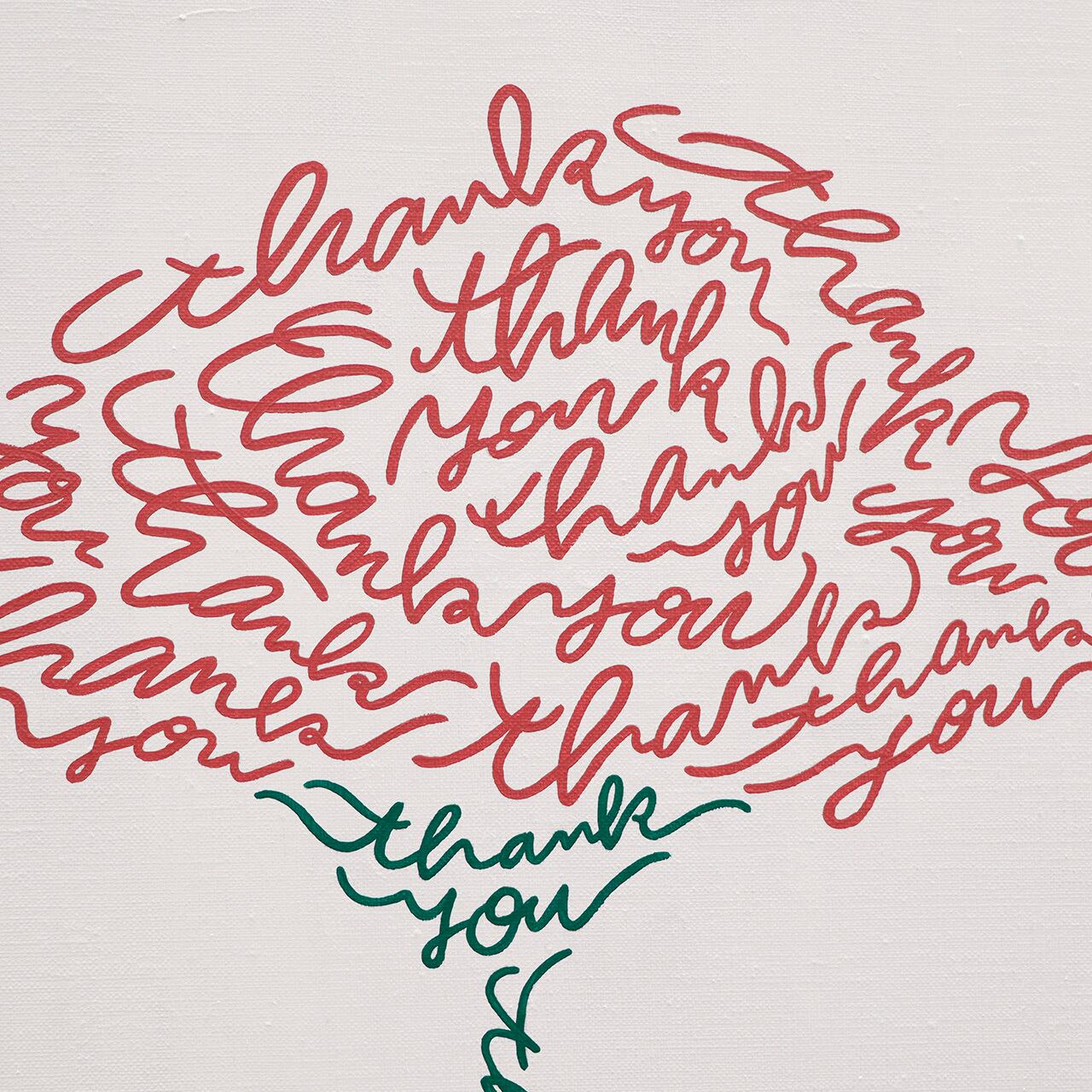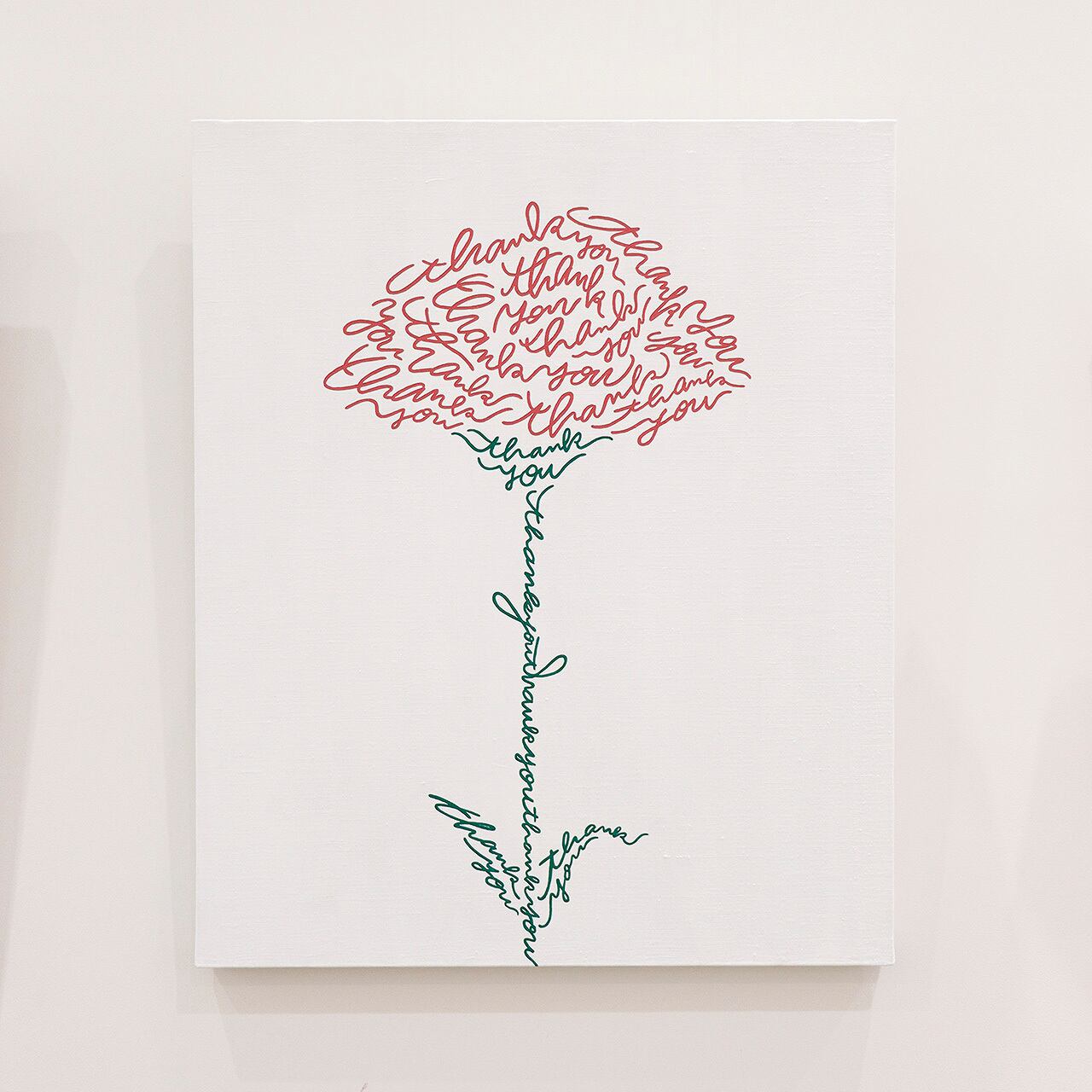
words flower 004 / thank you
2023年12月に開催した個展「PRESENT FOR」のメインビジュアルとなったバラの隣に展示したカーネーション。
プレゼントをもらったら「ありがとう」なので「thank you」です。
ピンクのカーネーションの花言葉でもあります。
全て筆記体の「thank you」で形作っています。
近くで見た時の花びらや葉の動きにご注目ください!